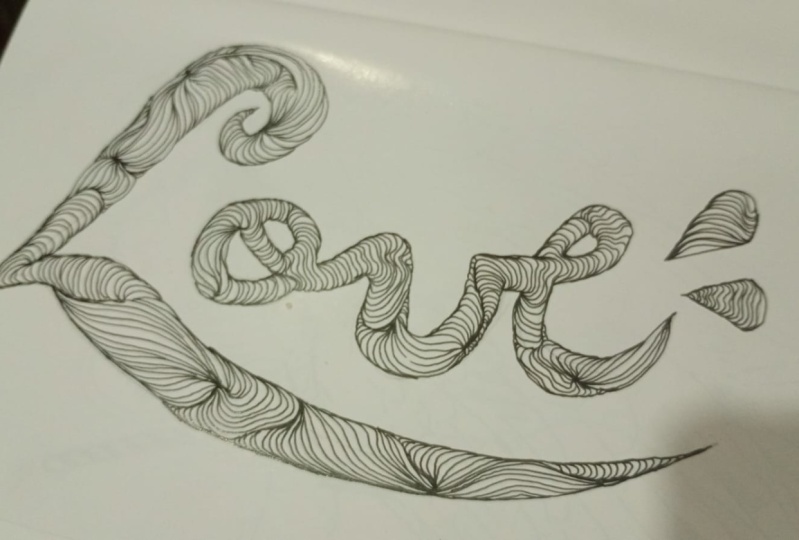
Faça uma tipografia tipo doodle
Introdução
Como preparar a base de contrário
Escolhendo a palavra e fonte
Como cortar o estêncil
Pensando em rabiscos
Como planejar os padrões na madeira
Como desenhar os rabiscos 1
Como desenhar os rabiscos 2
Como desenhar os rabiscos 3
O grande revelar
Sobre este curso
Você gosta ao rabo em rab, de rab, Você quer ter a melhor capacidade para fazer uma tipografia do rabisco legal?
Neste curso, você vai aprender como transformar seus rabiscos em uma peça de arte. Você vai trabalhar em uma de contraria, escolher sua própria palavra e fonte e a medida em depois fazer um estêncil. Você vai ter algumas ideias sobre diferentes estilos de rab, criando movimento e fluindo com suas linhas e em em seguida, desenvolver seu próprio estilo.
Vamos se canalizar a a esa
1. Introdução: mas começou. Eu sou alemão. Sou um artista e professor com sede em Wellington, Nova Zelândia. Tenho ensinado nos últimos 13 anos para estudantes do ensino médio. E ao longo desses anos, eu tenho trabalhado algumas maneiras realmente excelentes de explicar as técnicas em habilidades que os alunos precisam para desenvolver seu próprio estilo de trabalho neste curso fazendo tipografia. Vou mostrar-te como criar um pedaço muito interessante de cima de um pedaço de madeira, alguma tipografia e os teus rabiscos vão fazer um estêncil para a tua palavra. E eu vou mostrar-lhe como desenhar seus rabiscos através do estado para a peça de trabalho . Então, se você gostaria de criar um pedaço de Eu gosto deste e papel no curso de hoje e vamos começar a rabiscar 2. Como preparar a base de contrário: só quero encontrar ah, belo pedaço de madeira compensada que você deseja usar para o seu durante. Hum, você quer Teoh? Apenas descubra o tamanho que você quer. Você vai estar em forma e apenas governar isso na primeira pizza e estar apenas usando uma dor de escola e alguns grampos apenas cortar as bordas para baixo. Agora é bom se você pode usar um contraplacado leve porque o contraste bem com a entropia preta que vamos usar, basta enviá-lo fora. Eu tenho uma lixadeira orbital aqui, mas você pode fazer isso com o envio manual também e apenas dizendo que as praias descem bem. Então é apenas agradável e suave. Você não vai me dar lascas ou, você sabe, meio feio. Cada um está nele. Diga um pouco para baixo até ficar feliz com o que parece. Se preferir. Você pode usar papel para isso, mas eu gosto muito do olhar fora do grão de madeira, o chef de madeira teca por trás do desenho. E acho que se contrai muito bem com as linhas negras o que vamos desenhar mais tarde. Se você quiser usar papel, então basta encontrar um pedaço de papel de boa qualidade que você pode usar papel Catterick para imprimir papel e apenas obter que cafeína e leitura para o tamanho que ele queria fazer você se juntar. 3. Escolhendo a palavra e fonte: Tudo bem, agora vamos criar suas tomadas que vamos usar para o nosso projeto. Então nós queremos fazer é abrir uma loja de fotos ou se você não tem companheirismo, você pode usar Mark. Parar foram Ou o que se você gosta, criar um novo documento. E queremos que o documento seja do mesmo tamanho que o pedaço de madeira que usamos. Então minas 50 centímetros de largura, 23 centímetros de altura, e pode ser apenas uma imagem em tons de cinza. Por isso chama-lhe o que quiseres. E este é o tamanho do mundo. Então a próxima coisa que eu quero fazer é você quer desculpar um tipo têxtil na palavra que você quer usar, você pode usar qualquer lugar que você gosta no meu exemplo pode ser útil. Não conseguiria. Então, um, apenas no maior que como este no meio. Agora, se você quiser usar uma fonte muito simples, limpa e negrito sendo preto aéreo é muito divertido de usar. Esta é a diversão aqui mesmo. Você quer pensar em usar um formulário? Mas aqui está um pouco de peso para os líderes porque nós vamos estar atraindo os rabiscos para o espaço nas letras e então nós não queremos algo que é muito tipo de pele sua bagunça. E agora eu decidi que eu queria que Teoh tivesse um pouco de, ah, tipo ocidental de estilo frente para este design. E então eu não tinha nenhum lado divertido. Esse é Owen Teoh, um dos meus sites favoritos que fonte ponto com e é um ótimo lugar para obter fundos grátis. Hum, você pode apenas procurar em apenas um tipo de dar uma olhada inteira em torno de A com os diferentes temas. Mas eu fui para o tema ocidental aqui e apenas procurando, sentado, e eu me deparei com essa doutrina muito legal. Eu realmente gosto do golpe no K. Então eu baixei esse falso já caindo no seu livro principal. Quero dizer, realmente, para ir em uma loja filho. Então tudo o que eles querem fazer agora é apenas selecionar o texto que você tem tipo no nome da frente . Eu sou doutrina e coisa legal sobre este telefone é que quando você usa um K maiúsculo, você acaba com rapidez. Quero que algo seja muito legal. E o que ele é quando você tem esse direito. Basta redimensioná-lo para fazer com que pareça o tamanho que você quer olhar em sua peça de trabalho. Hum, não torná-lo muito pequeno. Caso contrário, vai ser muito difícil de atrair. Um, apenas uma espécie de fila no meio disso. Então isso parece muito bom. Agora, eu estou pronto para imprimir isso, e eu só vou imprimir em um par de quatro páginas, mas você pode imprimi-lo. Como você, tipo, realmente cortar estênceis? 4. Como cortar o estêncil: Tudo bem, então agora que temos impresso seria no papel, nós realmente começar a cortar o estêncil. Então, para este trabalho, vamos precisar que você pode usar uma faca artesanal ou você pode usar algumas ferramentas diferentes. Eu gosto de usar este bisturi para a rodada de áreas, e eu gosto de usar uma noite de artesanato reta para os anos seguidos. Então há muitas maneiras de fazer isso, e depende um pouco da culpa que você escolheu. Mas se você tem muitos anos seguidos, você pode apenas usar uma régua como esta e você pode apenas trabalhar seu caminho ao redor e apenas cortar todas as, uh, linhas retas como esta apenas andando e vindo assim. Agora, este em particular, nenhuma das linhas que está certo, eles são muito frios. Vou usar o bisturi para fazer este trabalho. Então o truque para fazer isso realmente é apenas uma espécie de segurar no papel e apenas puxar para baixo tipo de para você mesmo e apenas usá-lo como um p importante, como uma dor e apenas uma espécie de torcê-lo e você pode mover sua mão também. Tão fácil, porque é um papel muito fino. Você realmente não precisa pressionar muito para obter uma parte e um inferno meio louco . Você sabe, você faz seus cortes realmente até você. Não significa isso se não for perfeito. Mas obviamente, quanto mais perto você chegar das tomadas, melhor vai parecer no final. Tudo bem, então vamos cortar, ok? Agora, quando você chegar a um dos líderes que tem um ritmo fechado como este, obviamente se cortarmos toda a ninhada, então nós vamos acabar perdendo a paz no meio. Então o que você precisa fazer é cortar um pouco, comprometer a paz. Então é assim que se faz isso. E você basicamente quer se conectar com a Serie aqui para o lado de fora aqui. Então você quer cortar um lado assim? E então você quer apenas deixar um pouco de espaço como este para que quando chegarmos para fazer o desenho no estêncil, nós vamos realmente, hum, hum, tipo de desenhar em torno dessa área e então quando chegarmos a esta pacífica apenas dobrar ele de volta e podemos desenhar os detalhes lá dentro. Tudo bem, vamos cortar o resto do mundo. Ok? Tão pequenas, áreas fechadas como o A na hora são boas para deixar apenas um conector. Mas o problema com esta grande teoria aqui é que se deixarmos apenas um conector aqui, então ele vai facilmente tipo de feijão ou quebrar. Então a melhor coisa a fazer é ter que se conectar. É o oposto do ing? E eu acho que fica bom quando o conector é uma espécie de parte fora da linha existente. Então, se não gostarmos disso e deixarmos um corte decente lá dentro e eles também iam inventar um aqui, vamos fazer um pedaço através como se estivessem. Então, quando o cortarmos, este pó branco no meio vai ter de lugares onde está ligado ao exterior . Tudo bem, vamos continuar cortando. - Certo , então agora temos o gado das letras, e mesmo que algumas delas se mexam assim, isso realmente não importa, porque quando puxamos por cima, Nós vamos ser tipo de segurá-lo para baixo enquanto vamos. Então agora nós realmente Teoh pegar um pedaço de madeira e alinhar os carrapatos Alinhar o estêncil na madeira 5. Pensando em rabiscos: Tudo bem. Então aqui nós temos nossa alma de estado apenas colada na madeira, e você só quer pensar sobre o posicionamento e apenas ter certeza de que temos um tipo de espaços iguais ao redor do lixo, dependendo de você sabe, a localização exata de sua palavra no jornal e tipo de como você quer exprimir. Mas é onde eu queria estar. Antes de começarmos a fazer os padrões, só quero pensar só quero pensarem rabiscos por alguns minutos. Então o que vamos fazer é deixar isso de lado por enquanto. Vamos começar com um pedaço de papel e vamos pensar sobre o tipo de rabiscos que queremos usar agora podem ser qualquer coisa que possam ser qualquer coisa. Mas eu tenho alguns tipos de regras ou diretrizes que eu sigo no meu trabalho que você pode querer usar, ou você pode apenas querer criar suas próprias pitons também. Mas uma das coisas que eu gosto de fazer é eu gosto de ter fluxo de movimento, então eu gosto de ter todos os meus padrões meio que fluindo de um para o outro. Então o que eu costumo fazer é começar com uma linha como esta, qualquer tipo de linha e, em seguida, todas as coisas desenvolveram a partir dessa linha. Então o que eu gosto de fazer, um dos pacientes que eu gosto de fazer, é uma espécie de braço e forma. É bom assim. E eu gosto de desenhar as linhas de desenho indo na mesma direção em ir para o mesmo ponto neste tipo de brinquedos semelhantes. Mas então com diferentes tipos de pontos sozinho aqui, e eu gosto de fazer as partes de canto um pouco mais escuras. Basta trazê-lo para atracar triste, um pouco carregado na minha cama. Ok, então eu tenho algumas outras formas. Então, por exemplo, eu poderia ter uma forma que era, tipo, esse tipo de forma de lágrima. Você pode ter outra forma de lágrima fluindo dessa. E então eu também posso ter linhas que saem dos outros pescadores também. Então, tipo de linhas fluidas como essa, hum, e eu tipo de desenhar essas formas no meio. No meio dos espaços, eu poderia preencher o valor, hum, um pouco apenas imaginar que um estava andando por lá, preencha com alguns pequenos círculos como este. Agora, eu tento não deixar que eu tente não deixar mais nenhuma linha esquerda então eu não iria querer cruzar a linha assim. Hum, eu sempre quero tipo de fluir de uma linha ou, você sabe, ir até uma linha, mas não tipo de passar por cima. Então, às vezes, neste tipo de formas, eu poderia ir e você sabe, algumas linhas de contorno para terminar com algumas linhas retas para que você possa fazer que quiser. Realmente? Você pode querer que o dedo do pé tenha algum tipo de formas de flores como esta, mas você pode dizer que de cada um dos espaços entre, de lá vem outra forma ou, você sabe, fora de seus fluxos outra linha como essa em que se transforma em outro pedaço de bater. Eu não gosto que Teoh use padrões diferentes e na verdade gosto de ter uma caneta. É meio que fluindo por trás de toda a palavra e isso faz com que todo o tipo de se encaixem muito bem e olhar muito bem juntos. A outra coisa que eu gosto de fazer é ter um ponto de partida. Então, digamos que este ponto aqui na entrada, construa todas as pétalas saindo dela em uma espécie de, você sabe, como um aumento ou que é como o epicentro do Piton, e então tudo flui de lá. Então, para este, este exemplo, pode ser um ponto aqui em algum lugar com, você sabe, as coisas estão fluindo por aqui. Quero dizer, esse tipo de sair daqui, mas todos eles meio que vêm de um, um ponto. Então talvez tenha um pouco de brincadeira com alguns padrões e veja o que você não conseguiu inventar . Normalmente tenho uns quatro ou cinco padrões que eu mantenho para todo o projeto. E você pode querer apenas pensar em algumas idéias no papel antes de começar a trabalhar em seu pedaço de madeira. Ok. Tudo bem, vamos começar. 6. Como planejar os padrões na madeira: Então, para este projeto, decidi que vou começar com um ponto no centro da palavra, e vou usar esse ponto para ter todos os meus animais de estimação fluindo. Então eu vou começar no K, e eu vou apenas escolher um ponto bem ali, e o que eu vou fazer é eu apenas vou desenhar algumas formas que fluem para fora dali. Então agora uma das coisas que você precisa fazer uma das coisas que eu faço é que eu desenhe por cima do papel também, e você pode precisar segurar o papel um pouco para que ele não se mova. Tudo bem, então apenas coloque um pouco mais de fita adesiva lá porque Stinson estava se movendo um pouco. E agora continuo a planear com o meu Petain. Então, usando o ponto central lá querendo tipo de desenvolver algumas linhas que vão se outros, você sabe, os pitons serão baseados nesses pontos. Ok. Então, como você pode ver, o ponto no meio vai ser bastante construído. Está indo. Teoh vai ser bastante escuro estavam no centro porque nós vamos ter montes de linhas chegando a ele. Então vai ser um ponto muito óbvio do qual tudo está fluindo. 7. Como desenhar os rabiscos 1: Então agora que eu tenho a minha multa básica fora, eu tenho algum tipo de estrutura para o meu projeto. Agora vou começar a preencher algumas das formas e você verá que eu tenho algumas canetas diferentes que eu gosto de usar. Mas eu vou trabalhar organicamente através disso. E então quando eu meio que ter feito a maioria das formas, então eu vou começar a construir formas menores em torno dele. Quero dizer, no recheio interno, com alguns padrões menores também. Tudo bem, então vamos fazer isso. 8. Como desenhar os rabiscos 2: Então, uma das coisas que você precisa pensar quando você está fazendo seus padrões é que não vai haver um esboço para as letras. É assim que a Aegis quer são os fins das linhas vão criar a linha do seu trabalho. Então o que você precisa fazer é, tanto quanto possível, você precisa tentar e ter as linhas terminando na idade fora dos litros. Então este é um bom exemplo aqui porque quando levantamos o estêncil, você engana muitas linhas retas, muitos grãos que criarão a linha fora da borda. Você quer evitar esse tipo de coisa aqui, onde você tem uma espécie de linha que vai ao longo da borda e, em seguida, até cada um só porque não parece tão bom. Portanto, não importa se você tem alguns desses, mas, tanto quanto possível, tente trabalhar seus leões até o limite. Então, tudo bem, vamos continuar durante 9. Como desenhar os rabiscos 3: Tudo bem. Então, uma vez que você tenha feito uma área inteira ao redor da peça onde você tem os pedaços condenados, então o que você precisa fazer é agarrá-lo. Bisturi . E você precisa fazer um corte muito bom aqui. Apenas tenha muito cuidado para não ficar com a madeira. E você só faz isso. Na verdade, você pode cortar os dois. Oh, e então você só precisa terminar o padrão por aí. Especialmente na parte de dentro. E o mesmo com aqui? Não, um duplo aqui. E o truque é manter isso no lugar, então certifique-se de que está alinhado e eles terminaram. O paciente aqui meio que vai direto nessa linha. Quero dizer, podemos tirá-lo. Bem, uh, nós temos um juiz, e é muito legal porque você tem que ter uma pequena prévia sobre como cada um vai parecer quando a coisa toda terminar. Então agora só queremos o dedo do pé. Basta levar a chave para isso, mas é pouco antes de você fazer o conector. Mas você tem que fazer o tipo de tudo por aqui e depois cortá-lo e depois terminar aquele pouco enquanto você está segurando. Tudo bem, vamos continuar. Ok, 10. O grande revelar: Certo, agora que terminamos todo o padrão, podemos tirar o estêncil para a grande revelação. E lá estamos nós. Temos tipografia de rabiscos. Você pode ver como é muito fácil de ler no dia. Uma das coisas que eu acho que faz parecer um pouco melhor é se você tem algum tipo de áreas escuras ou algumas áreas mais construídas, e eu realmente acho que isso foi muito bom, porque ele apenas dá um pouco mais de peso. E as áreas que têm os leões que tipo de, você sabe, que realmente não definem o comer três. Bem, isso não importa muito, porque, você sabe, é meio que feito pela restauração das linhas também. Então, dá-lhe uma espécie de sentimento orgânico. Cada um agradece por fazer este curso. E eu espero que você goste durante o seu queijo tipografia doodle